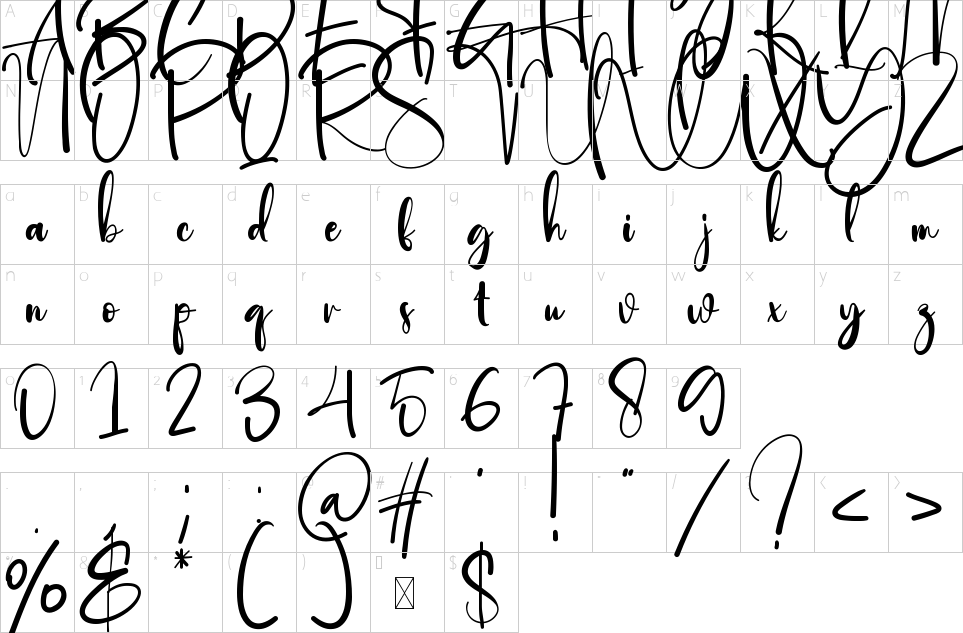
A Astrography Font é uma elegante e sofisticada fonte que oferece um toque distinto a qualquer projeto gráfico. Criada pelo designer scratchones, esta font foi projetada para os amantes de design que buscam um charme único para seus documentos e projetos de design. Desenvolvida para atender tanto as necessidades do Windows quanto das plataformas Mac, a Astrography Font traz uma graça moderna aos seus textos, permitindo que você personalize a aparência de sua página com um toque único. Com seus detalhes meticulosamente construídos, a Astrography Font é um recurso valioso para designers que buscam um estilo distintivo sem comprometer a legibilidade. Com 619 downloads, a Astrography Font já ganhou um reconhecimento significativo, e agora está disponível para que você a aproveite e personalize seus próprios projetos.